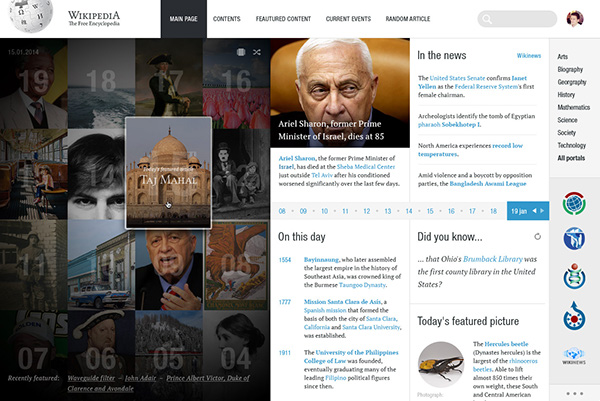
(Fiktive) Neugestaltung der Wikipedia
Ich bin gerade über Twitter auf diese fiktive Neugestaltung für die Wikipedia gestoßen und muss sagen es gefällt mir auf den ersten Blick recht gut.
Im Vergleich zur aktuellen Seite wäre das ein großer Schritt nach vorne. Bin gespannt, ob sich daraus was entwickelt und wollt mal hören, was ihr dazu so sagt?
So you wanted to show off your Photoshop skills? And you chose one of the top 5 websites? Surely nobody thought about it (both the project choice and actually redesigning Wikipedia).
[…]
But you’re missing the point of designing websites. And if you provide a Wikipedia redesign only to dismiss everything that made its success, and insert your own version of Dribbble’s latest trends, then you’re probably not worth hiring because you’re incapable of analyzing the core purpose of a project and tackling real-world problems.
[…]
And don’t call yourself a UX designer. You probably don’t know anything about UX. I know I don’t. Changing the color of a button to attract the eye is not UX. Whitespace is not UX. Oh, and not distinguishing visited from non-visited links is definitely bad UX.
So schön sowas immer klingt und anzusehen ist ... es ist immer nur schön und einfach, solange es fiktiv ist, und regt bei mir meistens das Nachdenken nicht über das jeweilige Gestaltungsobjekt an, sondern über Sinn und Unsinn von "Design"projekten, ohne sich mit dem Kunden und dessen Kunden auseinandersetzen zu müssen – also ohne Zielvorgabe, ohne Ansprüche, ohne bisherige Erfahrungswerte und ohne die Gefahr einer Überprüfung in der Realität.
Denn so richtig schwierig wird's ja erst, wenn es reale Anforderungen gibt, die erfüllt werden *müssen*, die Fakt sind, die man dem Kunden nicht ausreden kann, bei denen der Kunde mit seinen Anforderungen und Ansprüchen recht hat, und man muss sich ran setzen und das gut lösen. Man darf nicht die unbequemen 20% weg lassen, damit die einfachen 80% ungestört glitzern ...
Ich hatte grade vor kurzem eine Diplomarbeit in der Hand, die das österreichische Steuerformular für Arbeitnehmer neu gestaltet ... sah wirklich super aus, hat aber nicht das Steuerformular neu gestaltet, sondern das Steuersystem. Völlig am Ziel vorbei, schade.
Anderes beispiel das tolle, aber völlig unpassende, Microsoft-"Redesign" mit hochkontrastigen Mondkrater-Aufnahmen und einer einzigen Farbe für alles (und das Produktportfolio wurde auf 4 Anwendungen gekürzt) – so als würde Microsoft nicht drüber nachdenken wer sie sind und was sie anbieten, und daraus abgeleitet dann erst, wie sie aussehen (können).
Das soll jetzt nicht heißen, dass der Wikipedia-Entwurf per se schlecht ist – aber er innert mich ein wenig an ein National-Geographic-Jahrbuch, nicht an einen Informationscluster den ich mir erwarte, und er würde somit das Wesen der Wikipedia falsch darstellen. Es ist kein betreutes Magazin, sondern ein Informationshaufen in dem man wühlen kann. Wühlen ist hässlich, aber interessant, und die Wikipedia wird ja offensichtlich sehr gerne genutzt, also wäre es falsch, als Grafiker / UX-Gestalter erst mal ihr Grundkonzept zu hinterfragen.
Und die eigentlichen Probleme tauchen ja immer erst genau dann auf, wenn das dann umgesetzt wird,also nicht mit Modell-Inhalten arbeitet, sondern mit echten ... man kann dann Features weglassen, die für manche Nutzer essentiell sind (und bei der wikipedia is jede kleine Nutzergruppe groß) ... oder weniger zugänglich machen (die angepriesenen "rich interactions" sind schlimm für Leute mit anderen körperlichen oder technischen Bedürfnissen, und auch für Maschinen) ... oder es wird wieder "hässlich" wenn man doch alles reindrückt was man vorher weggelassen hat damit es einfacher aussieht ... oder man tauscht einen zukünftigen Vorteil gegen einen jetzigen Vorteil ein und macht ein Nullsummenspiel ... oder – speziell im Falle Wikipedia – die Stil-Vorgaben z.B. für Fotos und Infografiken lassen sich den Inhalte-Erstellern nicht aufzuzwingen bzw. nie auf das schon hundertausendfach bestehende Material übertragen  (Allein der weiße Text auf den glücklicherwiese immer schön gleichmäßig dunklen Bildern, oder das tolle Berlin-Panorama das auf volle Fensterbreite über dem Text tront ... das scheitert bei echten Daten mit großer Wahrscheinlichkeit bei der allerersten automatisch generierten Anwendung ... das kann nicht das Konzept sein).
Die Wikipedia-Ausgabe ist tatsächlich konzeptionell und technisch sehr einfach gebaut (und hat sich dahin evolutioniert), und das macht sie sehr flexibel im erstellen und im nutzen – für alle möglichen Menschen, für alle möglichen Maschinen, für alle möglichen Anwendungsfälle.
Ich für mich habe mir die Anzeige mittels Browser-Styling minimal so adaptiert, wie sie mir passt (z.B. etwas breitere Seitenränder, eine schöner gehintete Schrift), aber das möchte ich niemandem anderen aufzwingen, es würde seine eigene Nutzung des Datenhaufens unter Umständen einschränken.
Ich bin ja selber ganz großer Gegner vom allgegenwärtigen Update-Wahn – aber wenigstens etwas aufhübschen könnte man Wikipedia ja wirklich, dass es sich nicht mehr ganz so wie 90er anfühlt. ^^
Grad auch was die typografische Qualität der Artikel anbelagt: wenn man mal schnell was nachschlägt hat man auf nem großen Monitor dann halt im Vollbild mitunter 40 cm lange Zeilen mit 30 Wörtern oder so … Ziemlich weit weg, vom 8-bis-12-Wörter-langem-Idealstandard. Ich passe mir auch die Schrift immer noch bisschen an – der Rest: ist halt Wikipedia wie wir’s kennen.
Das Gesagte betrifft jetzt die Artikelseiten. Alles andere benutze ich halt nie, weil … ja weil mir das zu unübersichtlich ist und ich damit nichts anfangen kann. ^^
Sicher ist es nicht ganz leicht, eine so komplexe und im wahrsten Sinne vielseitige Hommage wie die der Wikipedia neu zu gestalten und das das ein Elfenbeinturm-Projekt ohne reale Anforderungen ist, hat besonders Sebastian ja schön dargelegt, aber trotzdem finde ich, dass die Wikipedia auch optisch etwas mehr her machen dürfte und sanft an die aktuellen Webstandards angepasst werden könnte, in dem etwa Media-Querries die überlangen Zeilen in großen Browserfenstern vermeiden.
Den Hinweis auf die User-Styles werde ich mir mal näher ansehen :-)